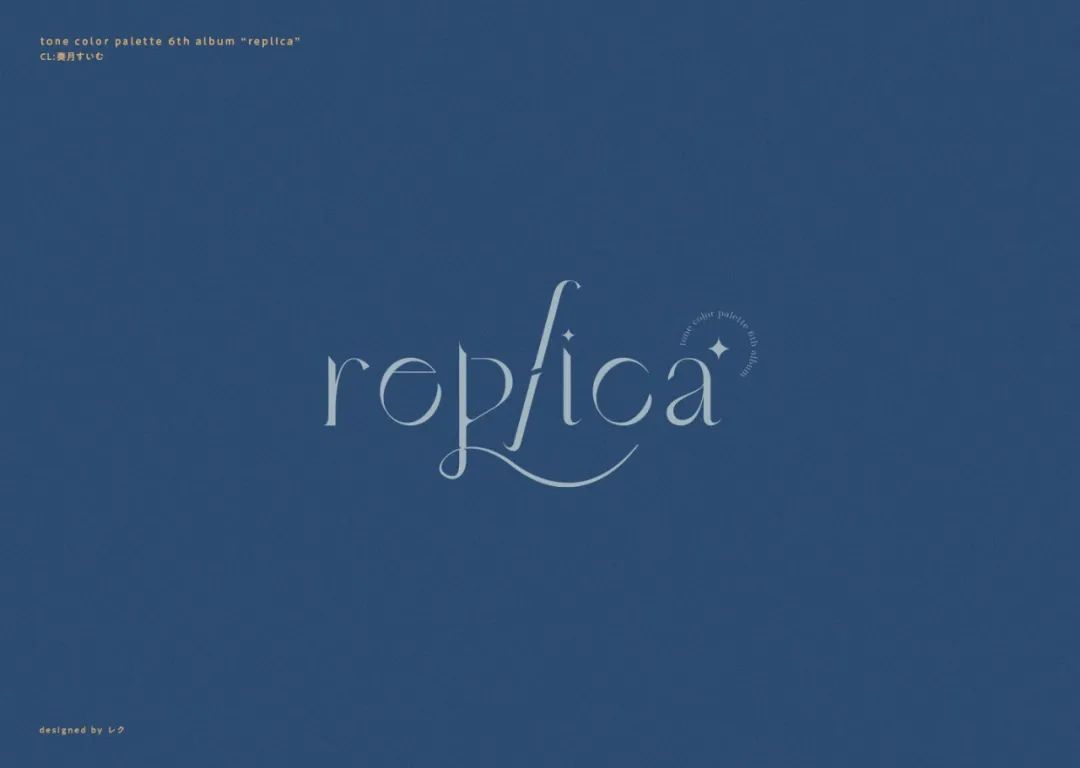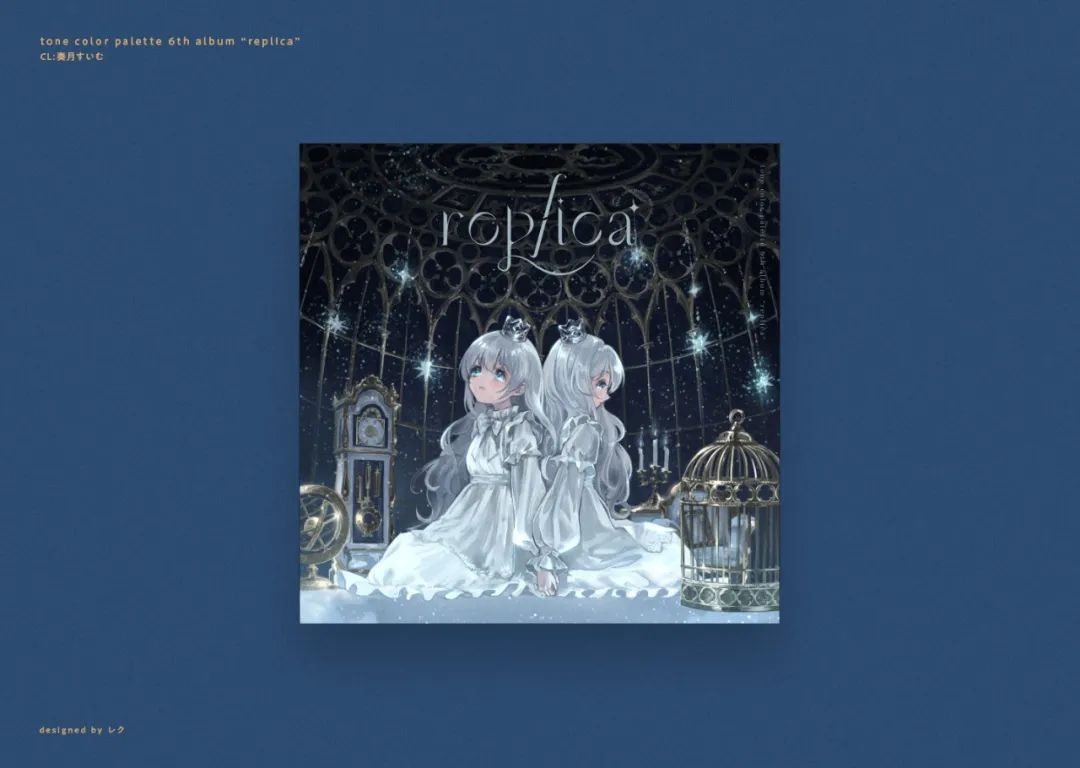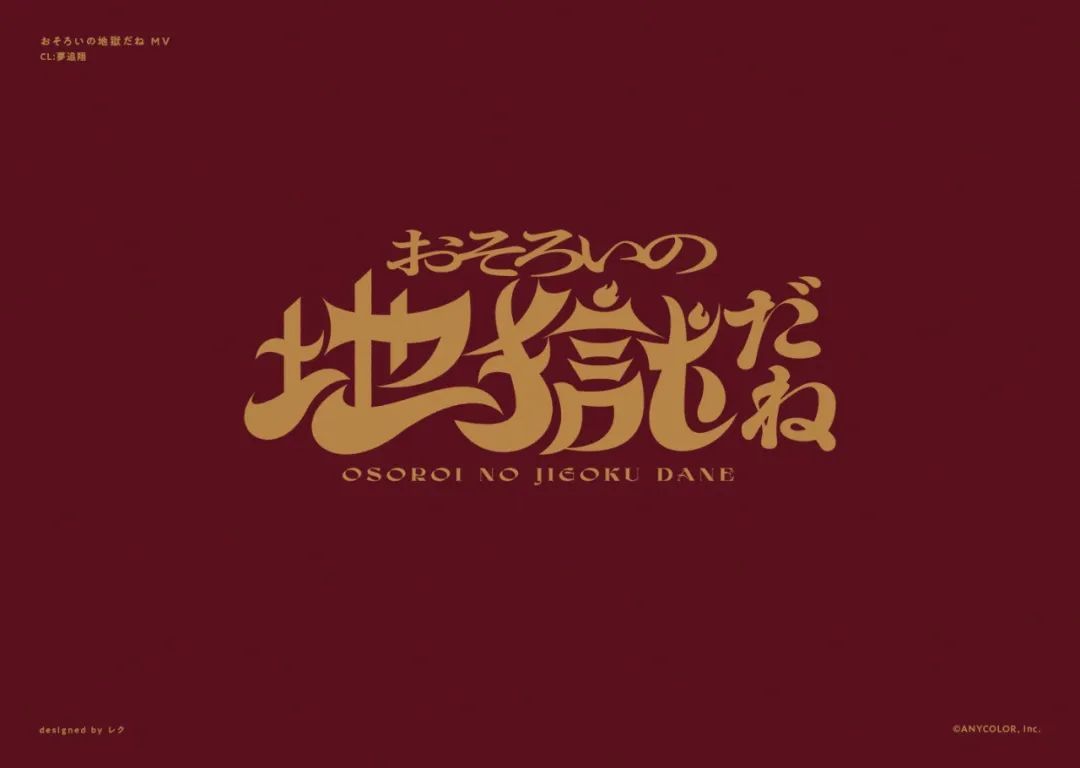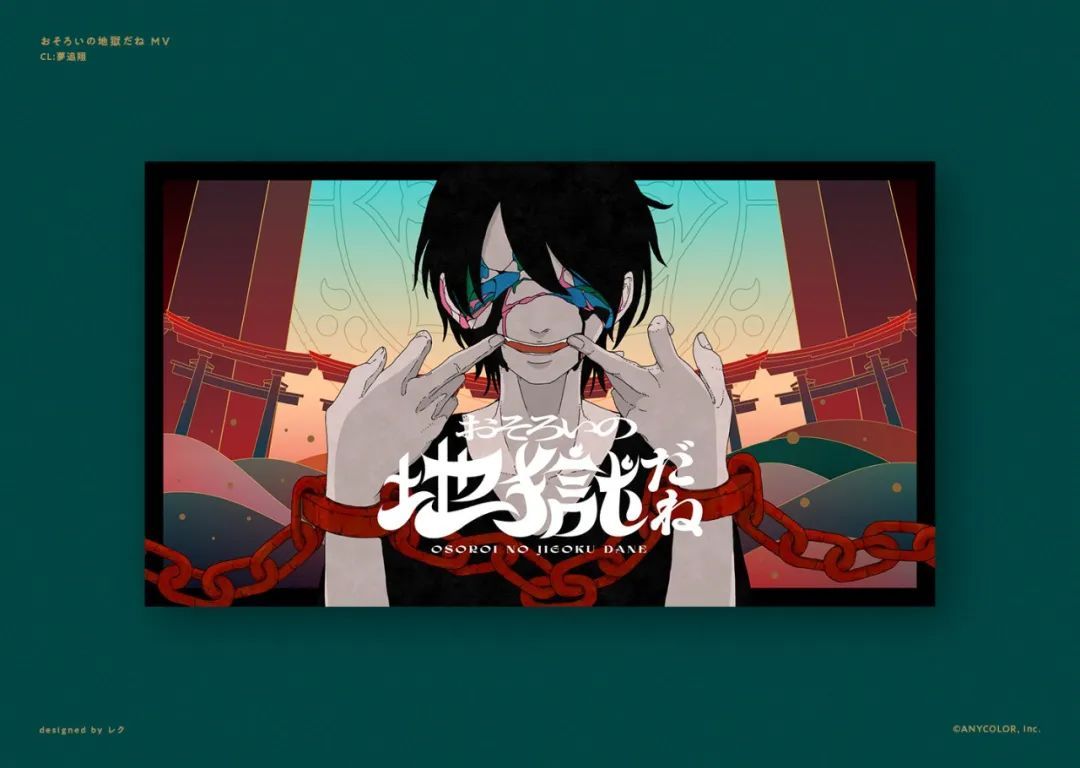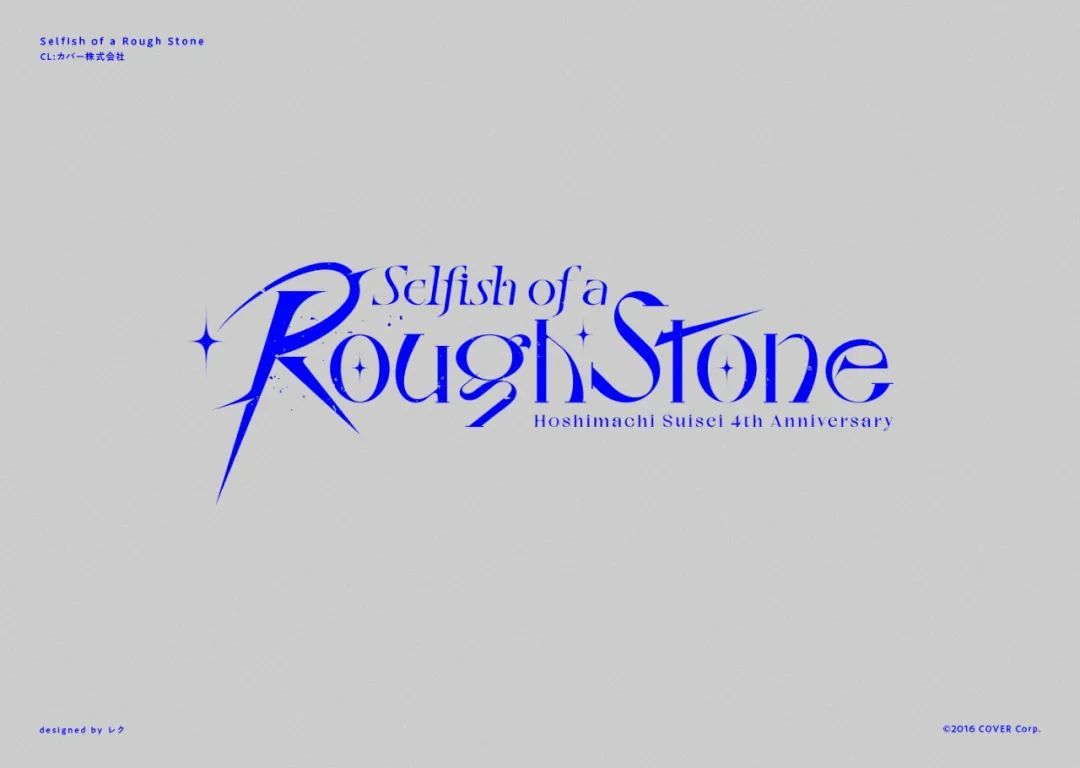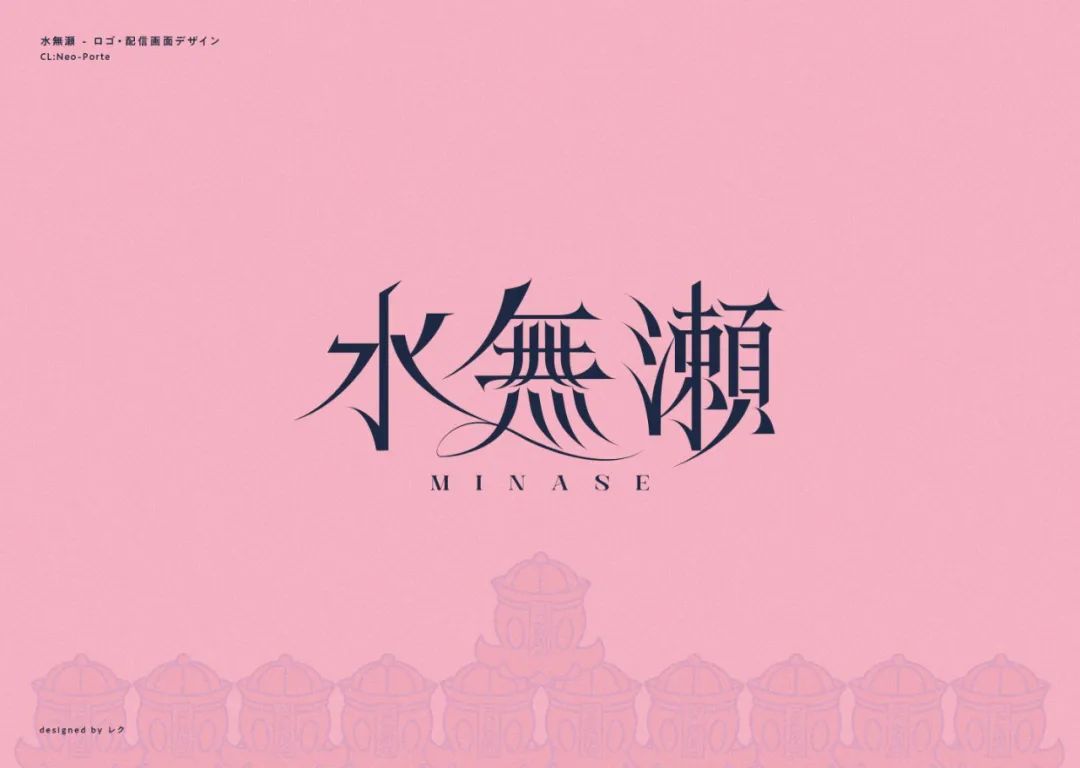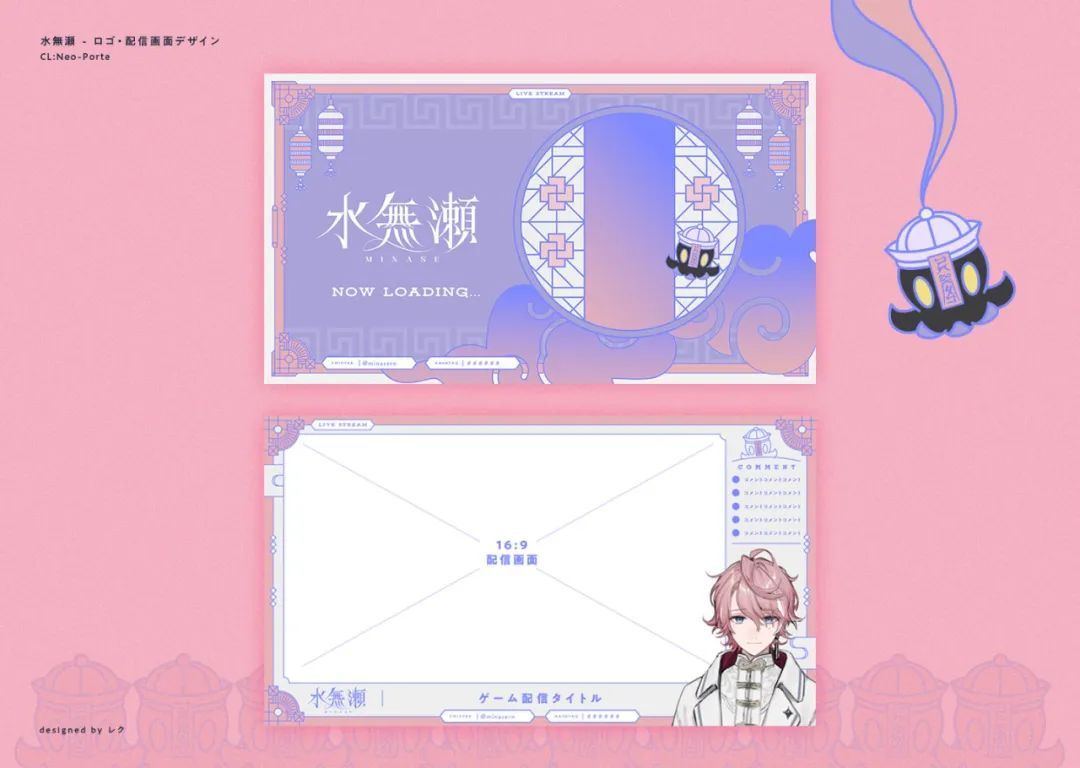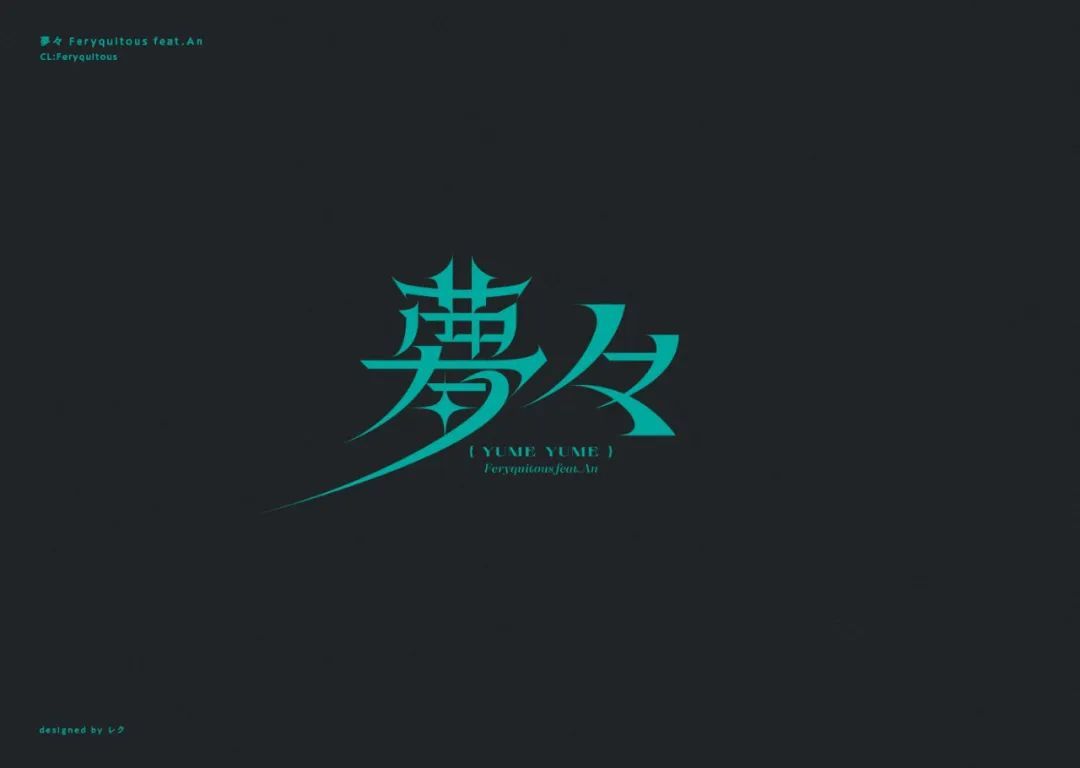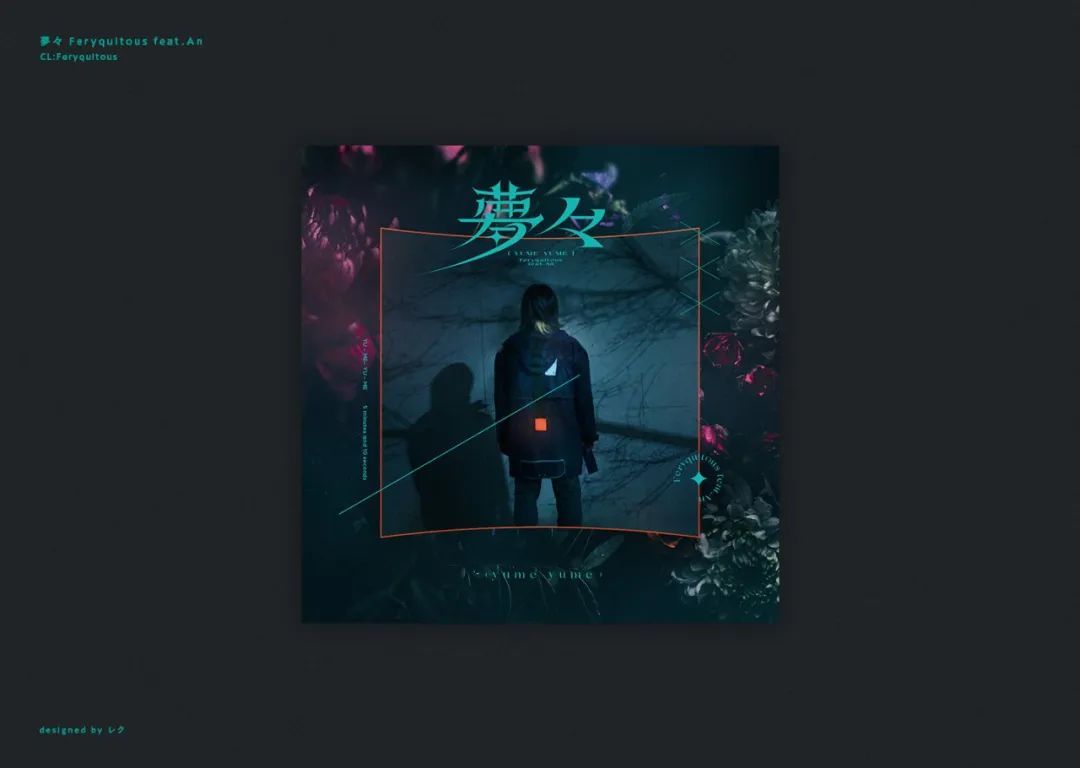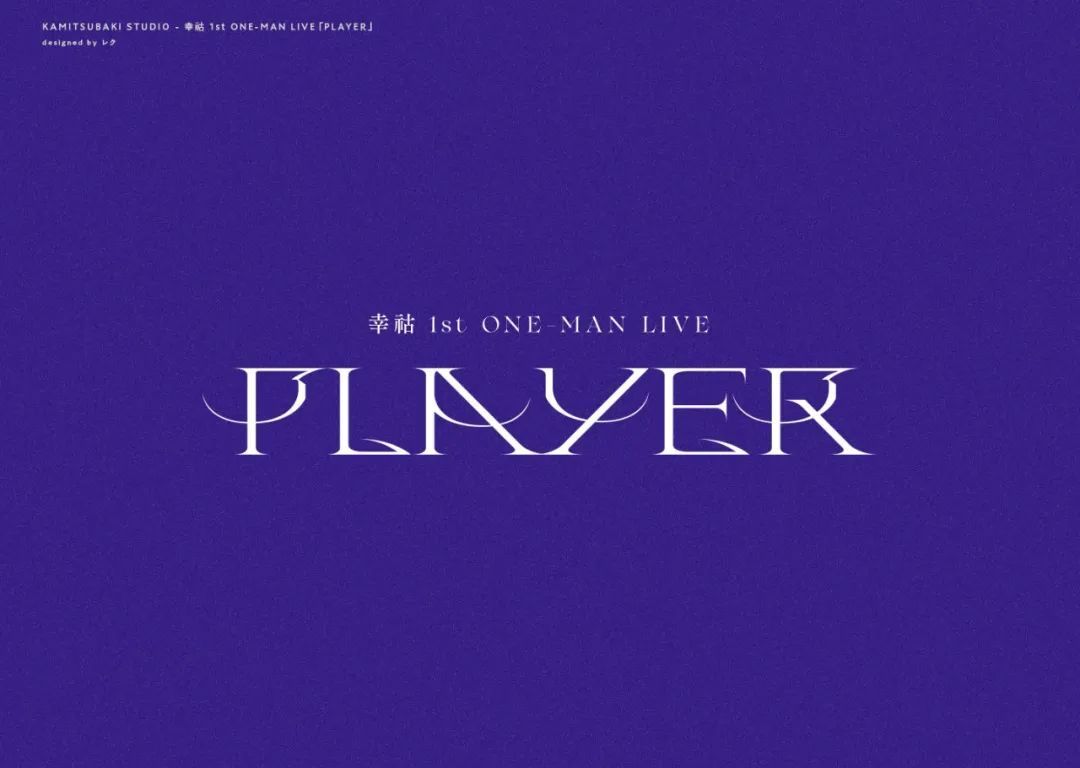
字体设计好了,如何应用到平时的设计中?
一副与画面、主题相得益彰的字体设计,往往能够起到突出设计主题,强化意境的作用。在现阶段的各个商业活动中,平面设计可以说是很重要的一环(海报、banner、广告设计等),而作为平面设计的重要组成部分,字体设计在其中的作用也是不言而喻了。
今天就同大家分享来自设计师 菅原 ヒロト的作品,其1992年11月出生于宮城県仙台市,看看 菅原 ヒロト 是如何将字体设计在动漫上应用的。
为 Suimu Sogetsu 的第六张专辑『replica』设计了字体标志。设计灵感来自于作品细腻的质感和概念。
『おそろいの地獄だね』MV 字体设计
为Hoshimachi Suisei的 星街すいせい4周年LIVE 『Selfish of a Rough Stone』设计了字体标志!
水無瀬字体设计!试图将一种感觉柔软的倦怠和中国风格的设计结合在一起。
为 Feryquitous 和 An 共同创作的歌曲『夢々』创作了标志字体设计。
1st ONE-MAN LIVE『PLAYER』,利用 Koko 强大的歌声及其图像和元素进行创作。
「prayer」type-W/B
负责"sasalasa"第一张专辑『LINNE』的包装Logo字体设计,设计它的目的是创造一种有机而有序的纹理。
制作了『怪物』的logo字体设计。用指甲撕破般的锐利感,加上文字扭曲的部分,表现出了动摇的心。
字体的大小、位置、粗细、间隔等等各种因素,可以通过设计完成不一样的视觉传达效果。当你了解了字体的基础性格,根据应用环境的不同去进行字体设计,可用不同的风格传达出不同的画面情绪。